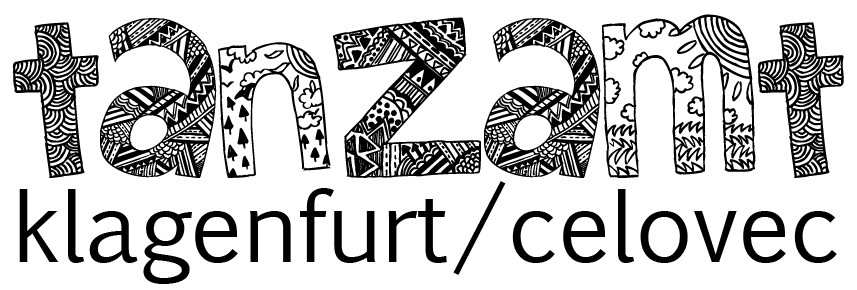
Welche Schriftart, welcher Font ist das? "Tanzamt"
Anbei ein Bild. Ich suche den Font mit dem "tanzamt" geschrieben ist.
Das "Innenleben" ist mit großer Wahrscheinlichkeit selbst hinzugefügt worden, aber die Kontur ist sicher von einem vorhandenen Font.
Hier ist das Logo größer:
Ich würde ernsthaft bezweifeln, dass es sich dabei um einen vorhandenen Font handelt. Ich vermute, die Buchstabenformen und die Füllung sind eine zusammenhängende Illustration.
Ja, diese Vermutung habe ich auch bereits. Jedoch, gibt es ein Plakat auf dem in der selben Art ein Schriftzug verwendet wurde. Nun lag es nahe, dass es eventuell einen "Grund"-Font gibt. Leider ist der / die Grafikerin nicht erreichbar.